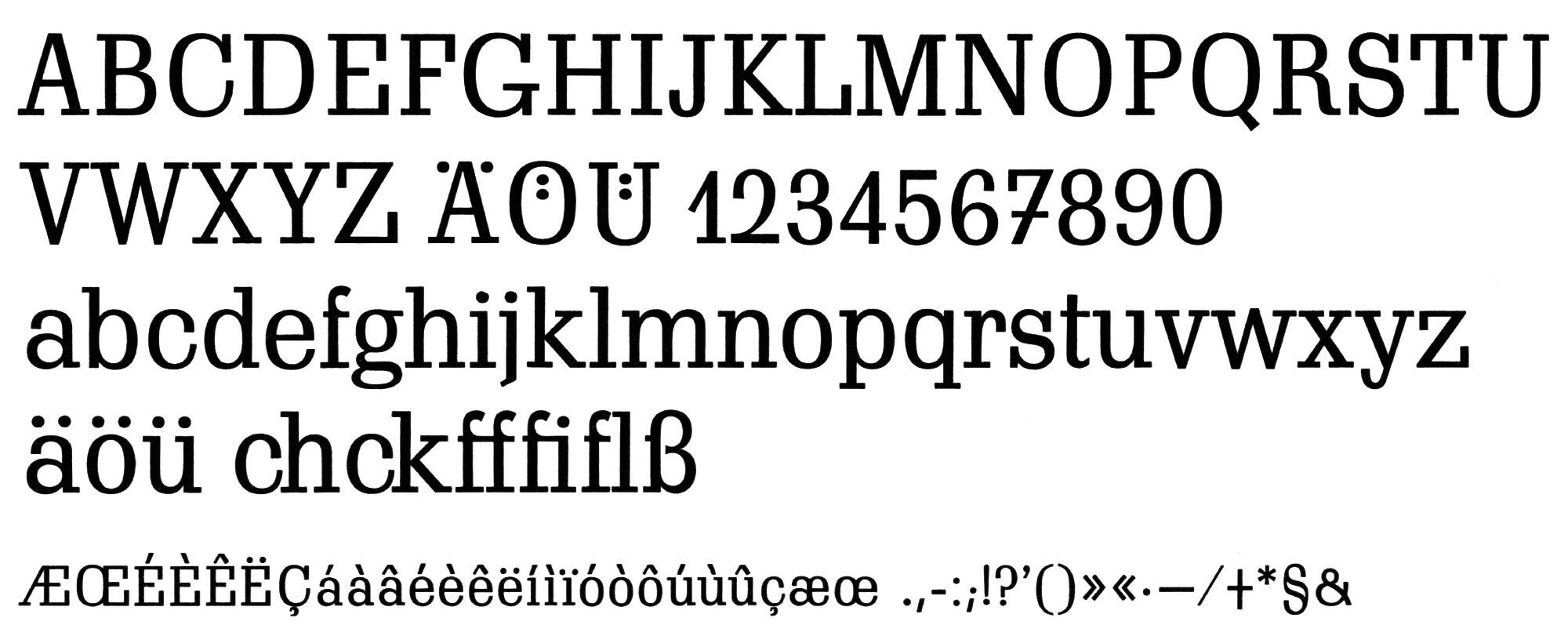
- 1938
- Antiqua statisch
»Charaktervoll, vielseitig verwendbar, klar und wirksam …« bewarb C.E. Weber die Schadow-Antiqua von Georg Trump. Die Schrift erschien ab 1938 und wurde in der Folge bis in die 1950er-Jahre hinein weiter ausgebaut. Der Skelett der Schrift ist eher statisch und klassizistisch, jedoch mit kräftigen, zu dieser Zeit recht beliebten Egyptienne-Serifen.
Für Schaugrößen-Anwendungen wurden aus den Versalien schattierte Schnitte entwickelt, die jedoch nicht unter dem Familiennamen der Schadow liefen, sondern unter der Bezeichnung Forum (I und II).
Eine Digitalisierung der Schadow in sechs Schnitten gibt es von Bitstream.